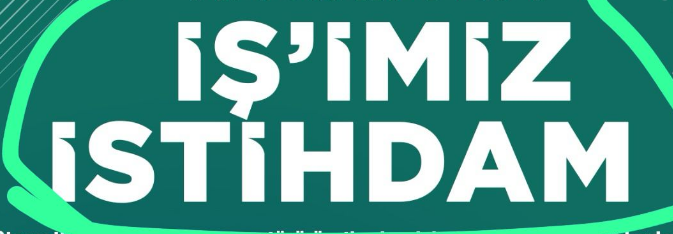
Font bulma yardım
Bu fontu bulabilecek var mı çok aradım ama bulamadım, benzeri var ama bu font yok
Font ismi Gotham fontu ancak font üzerinde tasarımcı düzenleme yaparak İ harfinde düzenleme yapmıştır.
Bunları bulabildi ama sanırım yanlış..
İnsanların gözü de kör bakar kör
Bunları bulabildi ama sanırım yanlış..
benziyor mu hocam
) değil bunlar.
Font ismi Gotham fontu ancak font üzerinde tasarımcı düzenleme yaparak İ harfinde düzenleme yapmıştır.
GOTHAM BLACK fontuna benziyor ama İ ler özel yapılmış gibi.
Merhaba hocam, fontun adı gotham, ancak yapan arkadaş i harflerinin üzerinde düzenlemeler yapmış. İyi çalışmalar.